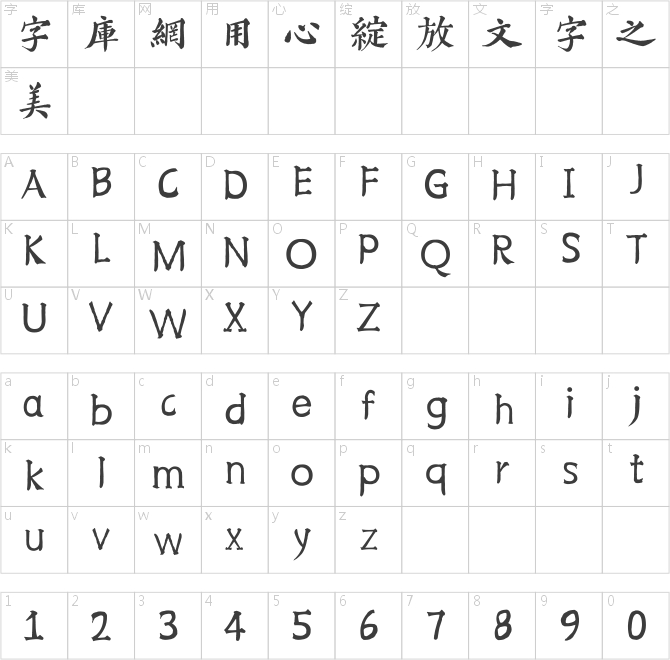
邯鄲(清)鄭孝胥千字文
邯鄲(清)鄭孝胥千字文介紹
鄭孝胥(1860-1938),中國近代政治人物、詩人、書法家。福建省閩侯人。1882年清光緒八年舉人,曾歷任廣西邊防大臣,安徽廣東按察使,湖南布政使等。辛亥革命后以遺老自居。1932年任偽滿洲國總理大臣兼文教總長。善楷書,取徑歐陽詢及蘇軾,得力于北魏碑。所作蒼勁樸茂。為詩壇“同光體”倡導者之一。